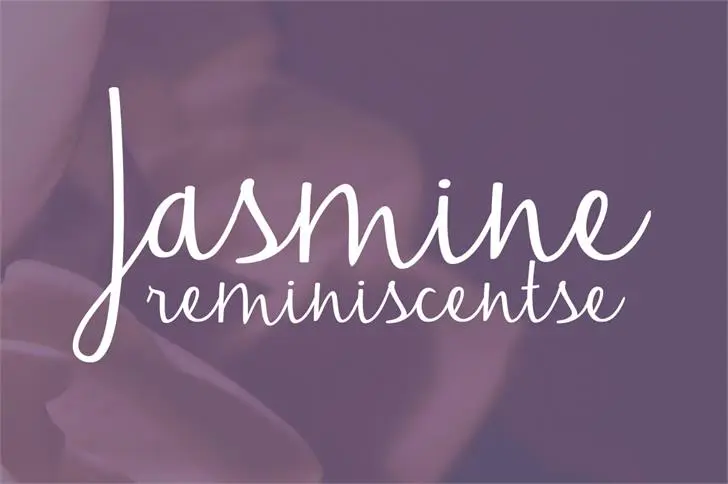
A Jasmine Reminiscentes é uma nova adição à famosa família de fontes Script, criada pelo designer britânico Hamilton. Esta fonte traz um toque de nostalgia e elegância às suas criações digitais, inspirado nos traços românticos da mão humana. Seja você criando cartões personalizados para sua empresa ou desenvolvendo uma marca visual única, a Jasmine Reminiscentes oferece linhas suaves e detalhes sofisticados que vão aprofundar o seu design. Com um estilo elegante que remonta ao passado, mas com as características modernas necessárias para uma aplicação em qualquer meio digital, esta fonte é perfeita para aqueles que buscam complementos que transmitem sutileza e história. Para conhecer melhor e fazer o download desta fonte maravilhosa, visite o site do designer no link fornecido.